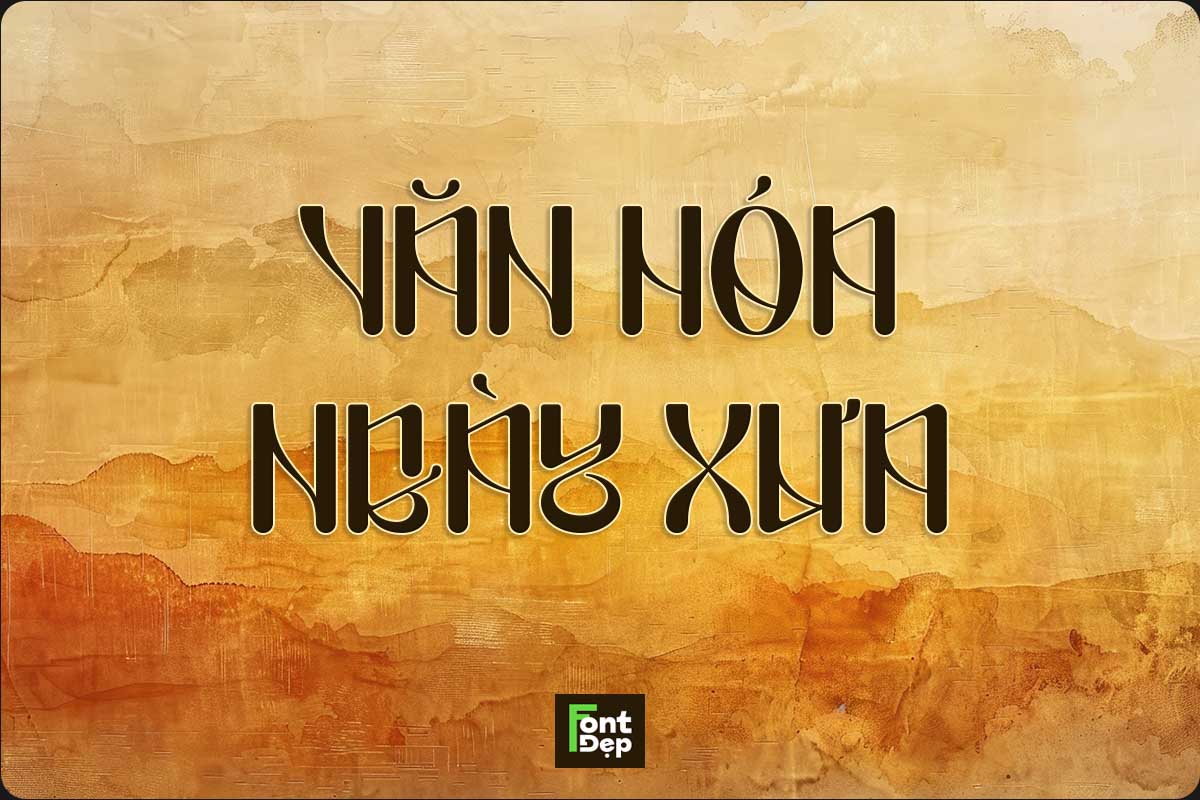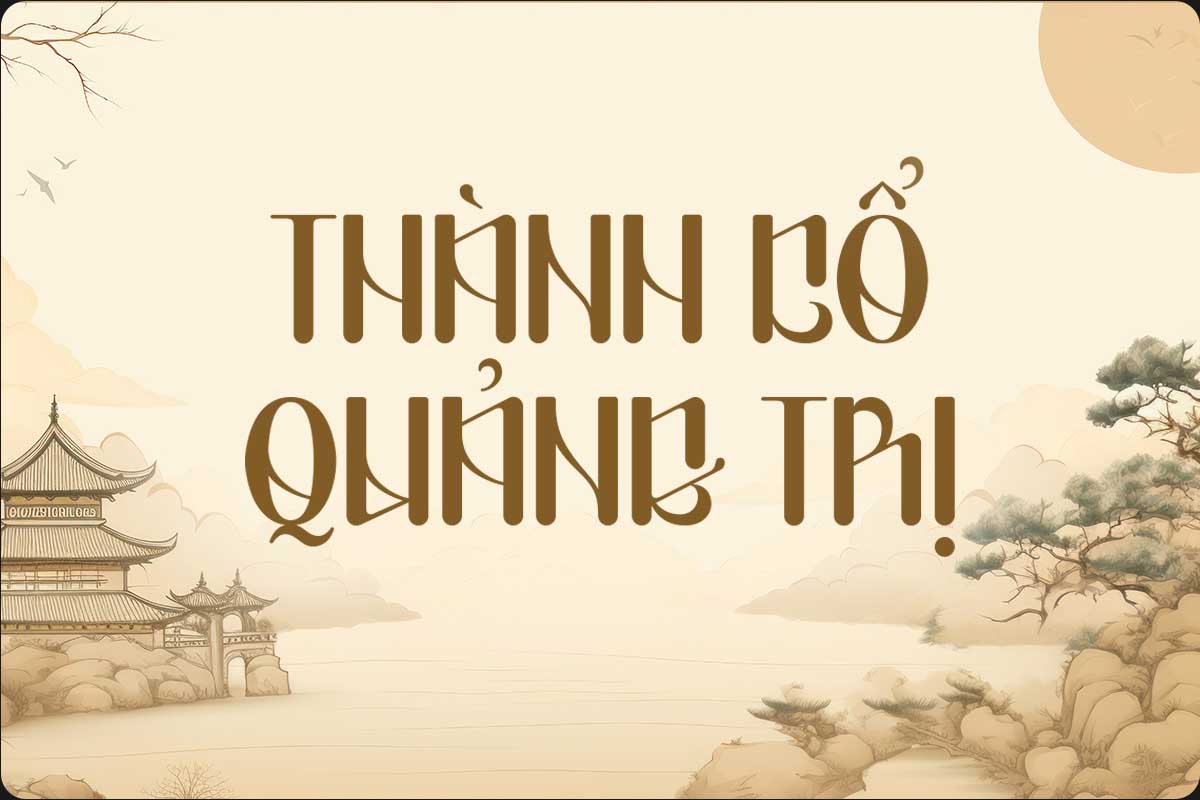
Font chữ đẹp cho lĩnh vực thiết kế cổ trang - SVN Nubya Việt hóa
Font chữ không chỉ là công cụ trình bày thông tin, mà còn là yếu tố tạo nên linh hồn cho thiết kế. Đặc biệt với các sản phẩm mang tính truyền thống như poster cổ trang, ấn phẩm văn hóa, bao bì sản phẩm thủ công – việc lựa chọn đúng font chữ là yếu tố quyết định cảm xúc thị giác. Và SVN-Nubya chính là một lựa chọn nổi bật trong số đó.
Phong cách thiết kế: Kết hợp truyền thống và hiện đại
SVN-Nubya là một font chữ sans-serif mang phong cách cổ trang độc đáo, được thiết kế bởi Ajax Piper và Việt hóa hoàn chỉnh bởi nhóm STYLEno.1 Fonts. Điểm đặc biệt của font nằm ở cách pha trộn giữa các nét tối giản hiện đại và cảm hứng từ thư pháp truyền thống – tạo nên một cảm giác trang trọng, tinh tế nhưng vẫn dễ đọc và dễ ứng dụng.
Các nét chữ của SVN-Nubya có độ dày đồng đều, đường cong mềm mại, không chân nhưng vẫn giữ được vẻ cổ kính qua từng ký tự. Đây là yếu tố lý tưởng cho các thiết kế như: tiêu đề phim cổ trang, bao bì mỹ phẩm thiên nhiên, sản phẩm thủ công hoặc các chiến dịch truyền thông về di sản văn hóa.
Việt hóa chuẩn tiếng Việt – Dùng thoải mái không lo lỗi dấu
Một điểm cộng lớn cho SVN-Nubya chính là bộ Việt hóa được thực hiện chỉn chu: đầy đủ dấu tiếng Việt, dấu thanh được đặt chính xác và hài hòa với từng ký tự gốc. Điều này không chỉ đảm bảo khả năng sử dụng linh hoạt trong thiết kế tiếng Việt, mà còn giúp nhà thiết kế tiết kiệm thời gian chỉnh sửa thủ công.
SVN-Nubya phù hợp với nhà thiết kế đồ họa, marketer, nhà xuất bản hoặc bất kỳ ai đang tìm kiếm một font chữ gợi không khí xưa cũ nhưng vẫn hiện đại, dễ ứng dụng trong các dự án truyền thông văn hóa, thiết kế sáng tạo, branding hoặc tổ chức sự kiện cổ phục.